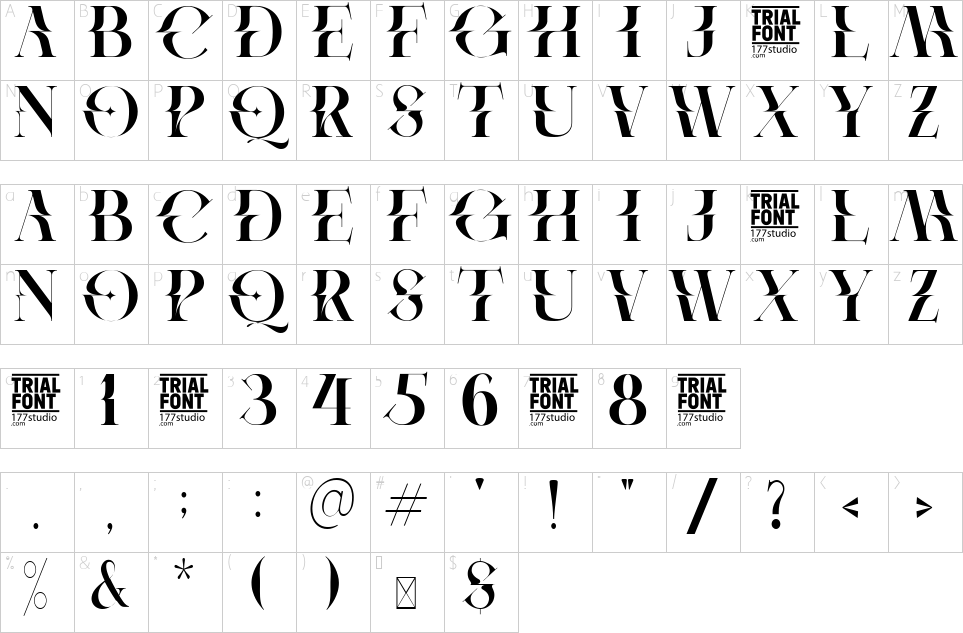
A fonte Protest é uma opção gratuita e versátil para designers gráficos, disponível tanto para Windows quanto para Mac. Desenhada por 177Studio.com, ela já foi baixada mais de 1,753 vezes por designers de todo o mundo. Protest traz uma dose forte de estilo, com linhas fortes e um peso forte que podem ser usados para destacar mensagens de consciência social e protesto. Se você está buscando uma fonte que possa expressar sua própria visão crítica ou deseja dar uma mãozinha ao próximo, a Protest está aqui para ajudá-lo. Ela é perfeita para criar design gráfico que seja tanto visualmente atraente quanto significativo.